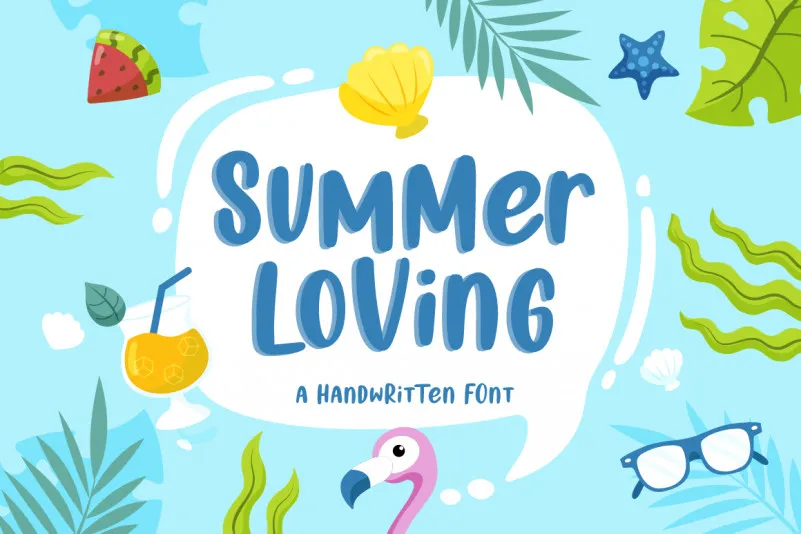
Summer Loving Display Font – Download Grátis
A Summer Loving Display Font é uma escolha ideal para qualquer atividade envolvendo crianças ou projetos escolares que buscam uma pitada de diversão e autenticidade. Essa fonte, com seu toque delicado e descontraído, não apenas traz um ar de leveza ao projeto, mas também transmite uma sensação de confiança genuína da infância. Suas formas suaves e cores vivas remetem à primavera quente que chega em abril, com seus dias mais longos e tons vibrantes de verde e rosa. Não importa se você está criando cartazes escolares, desenhando uma história infantil ou até mesmo fazendo propaganda para um projeto de festividade de crianças, a Summer Loving Display Font oferece os detalhes perfeitos necessários para capturar a atenção e o espírito da infância.